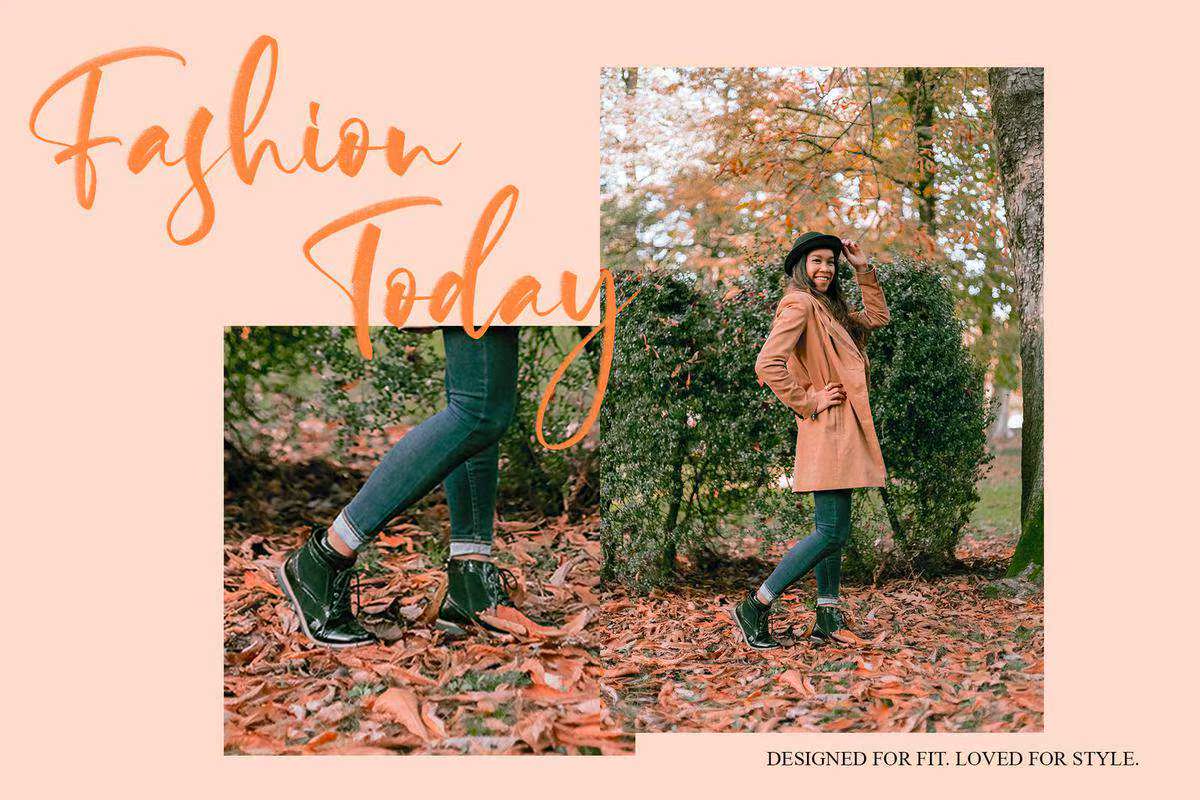
DaglathemisvGhandwrittensScript字体承载着热带的概念和每种字体的美丽,DaglathemFont完美地用于打印报价、婚礼宣传卡、社交媒体头条、产品包装等!DaglathemisvGhandwrittensScript字体承载着热带的概念和每种字体的美丽,DaglathemFont完美地用于打印报价、婚礼宣传卡、社交媒体头条、产品包装等!